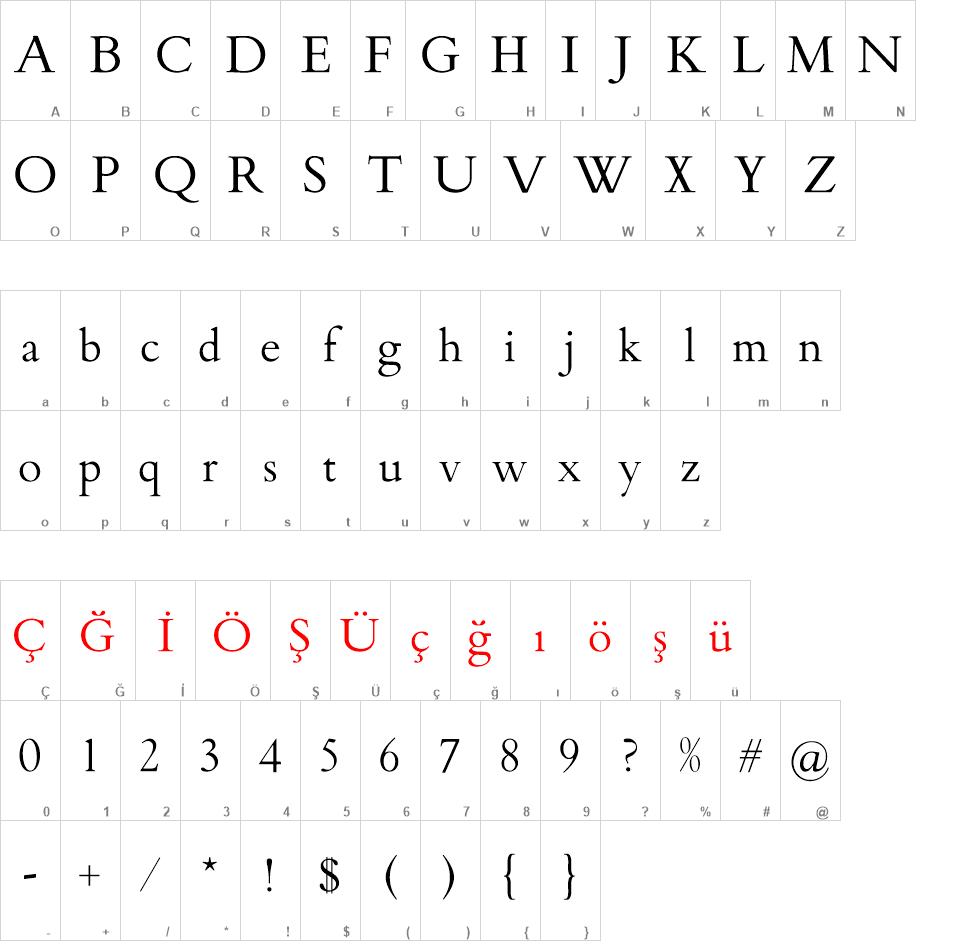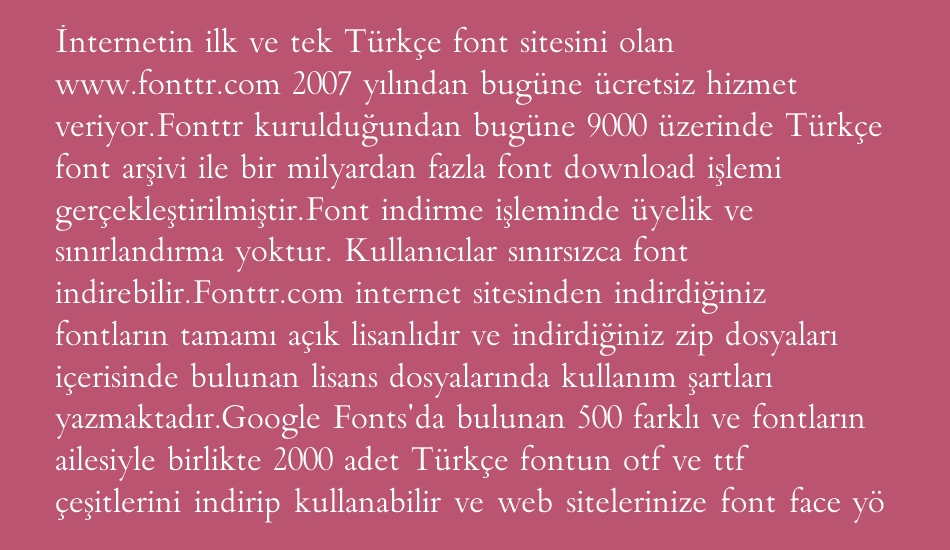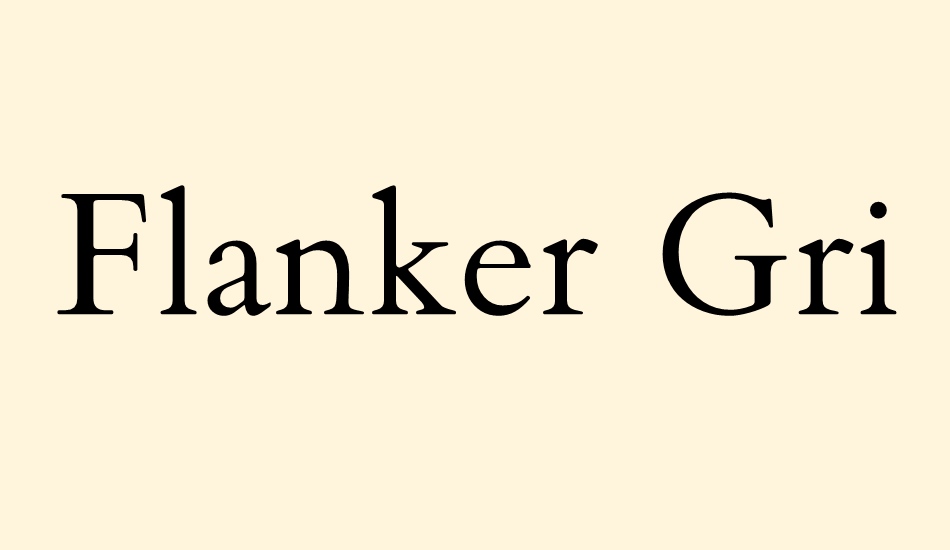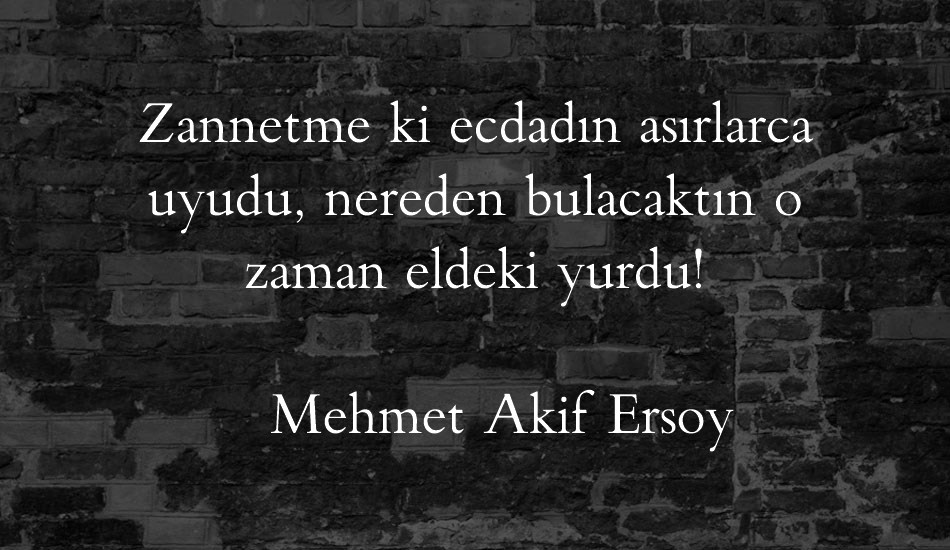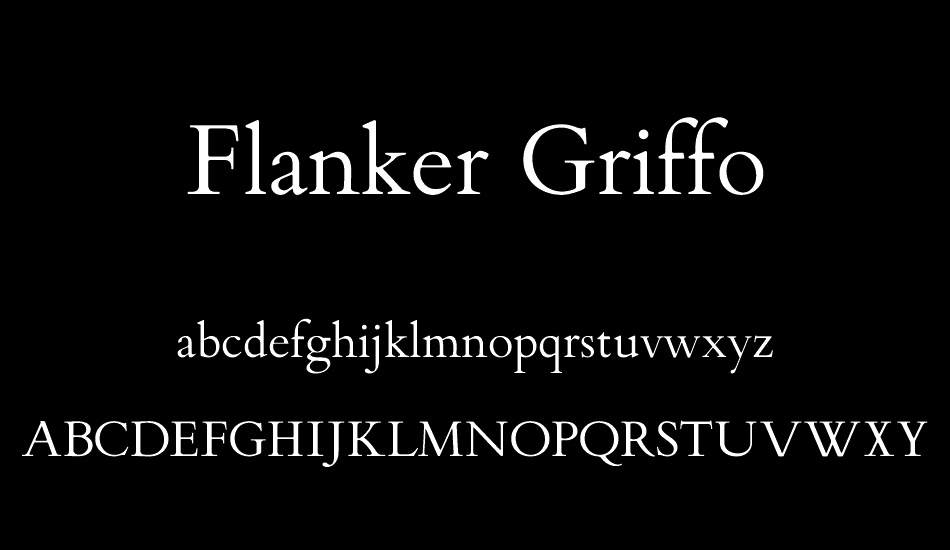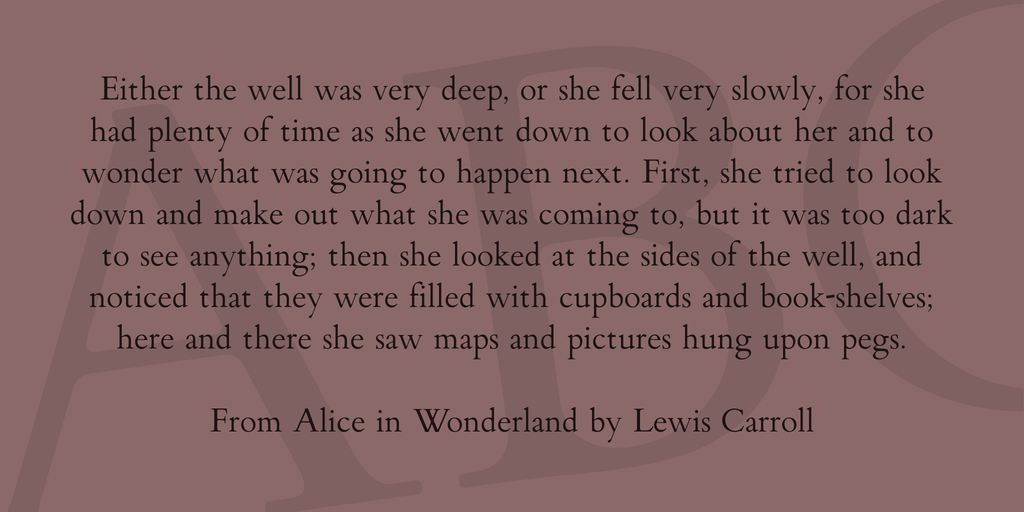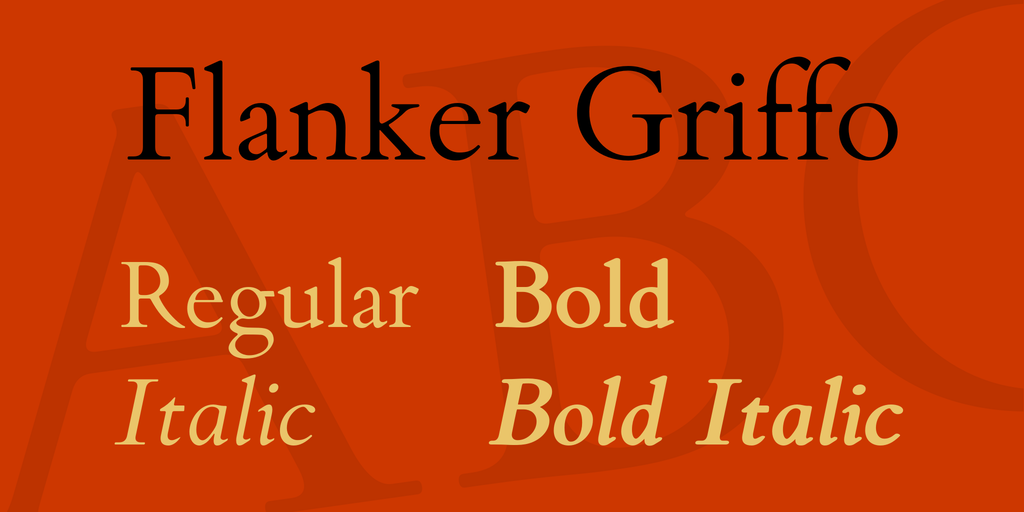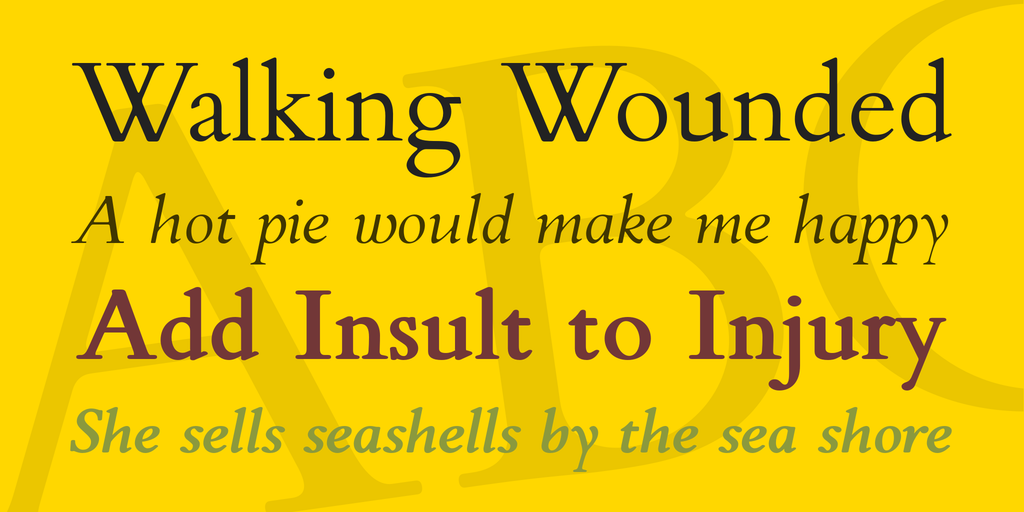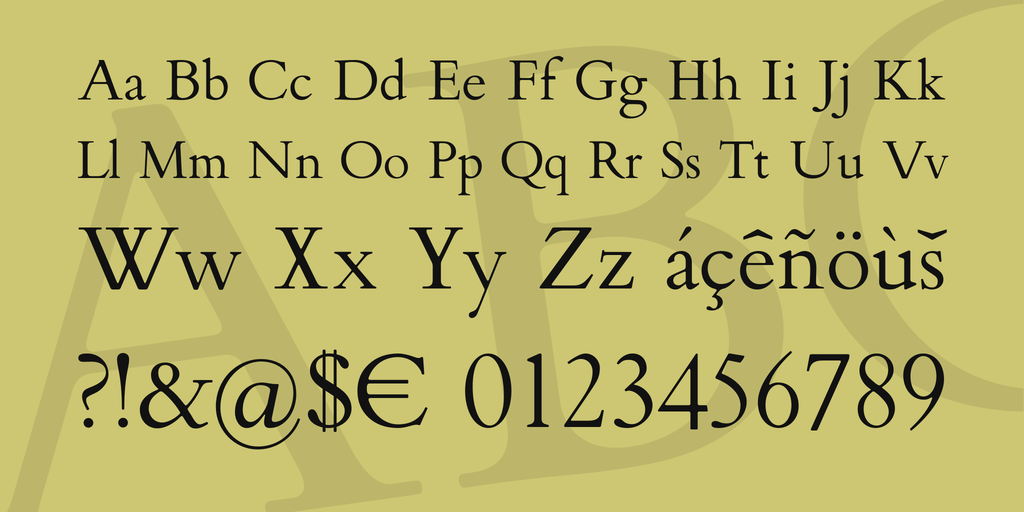
Flanker Griffo Font Family font
Flanker Griffo yazı. Harfleri serif, yüksek kontrast görünür, kollar ve büyük harf topa terminalleri arasındaki bağlantılar. Yazı tamamen PostScript eğrileri ve OpenType bitişik harfler ile güncellendi ve karakter aralığı. Ayrıca özel glif birçok yeni Unicode tablolara göre güncellendi.